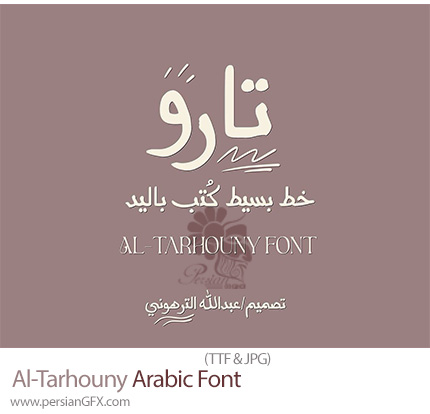
در این بخش شاهد فونت عربی تارو می باشید که با فرمت TTF بر روی سایت برای دانلود قرار گرفته است. Al-Tarhouny یک فونت زیبا و حرفهای برای طراحیهای عربی و اسلامی است که با سبک سنتی و مدرن ترکیب شده و مناسب طراحی تایپوگرافی، چاپ، تبلیغات و پروژههای دیجیتالی میباشد. اگر به دنبال یک فونت حرفهای و شیک عربی برای پروژههای خود هستید، فونت الطرهونی (Al-Tarhouny) انتخابی عالی برای طراحیهای مدرن و سنتی شما خواهد بود.